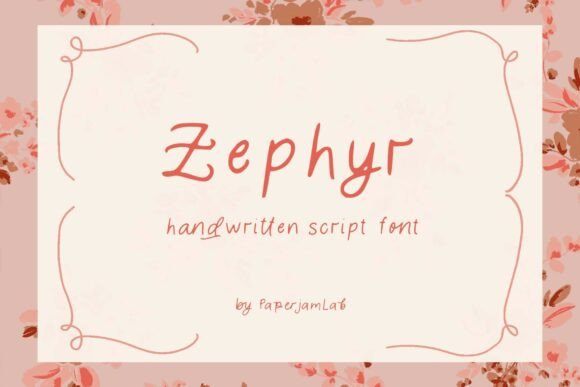
Zephyr
Zephyrのような高品質の素材をお探しの場合、このプレミアムパッケージはクリエイティブなプロジェクトに素晴らしい選択です。
精密に作られたZephyrは、クリーンなベクター、滑らかなタイポグラフィ、そして安心のための商用ライセンスを提供します。
POD(オンデマンド印刷)製品、結婚式の招待状、またはソーシャルメディアのグラフィックを作成している場合でも、Zephyrは理想的です。